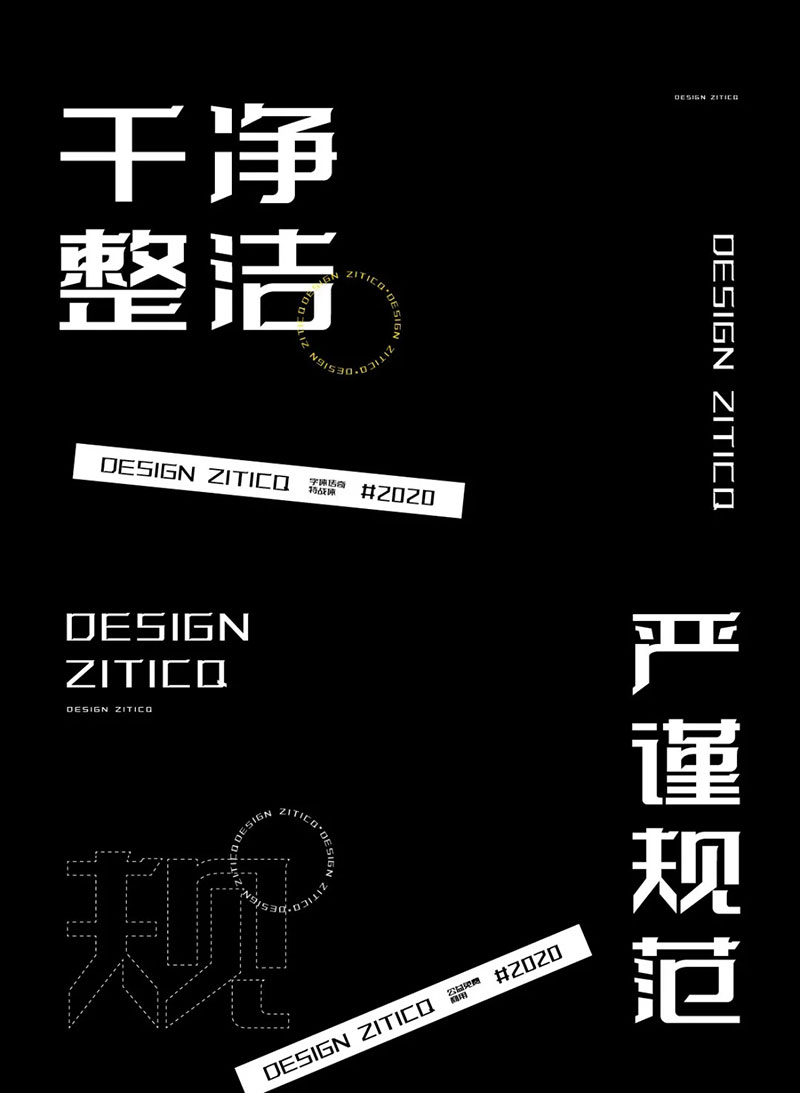
字體傳奇特戰體,根據GB2312編碼設計,整套字庫包含6763個簡體中文漢字,整體字形設計採用橫細豎粗的設計風格,橫線右端傾斜修飾,豎線右上角尖角修飾變形,整體視覺統一剛勁有力。
這款公益字庫,最早在2015年時,在群裡喊了幾十個人開發這款字,當時大家積極都挺高,給每個人分配好,要設計的字體內容後沒過多久,就聯繫不到參加的人了。可能是公益免費字庫設計,費時費力還不討好的事,這款公益字庫團隊就這樣散夥了。
直到2019年末,我才下定決心又在在群裡吆喝了一聲,做字庫的事情,這次我只找到了5位,願意做公益字體的小夥伴,其中有兩位是在家帶小孩子的小姐姐,還有兩位是一對情侶,一個在上班,一個在考研, 最後一個是00後的設計師,在加上我東拼西湊,這就是這個公益字庫的小團隊。當時正好趕到過年,大家都沒有出門,從初一下午就開始在設計,一直到五六月份才全部設計加修改完成。
沒有專職的設計團隊,就這樣湊齊了幾位小夥伴,一切都是熱愛設計才聚到一起,如果不是因為熱愛幾年前就放棄了這件事。由於人比較少,但做了一件很艱苦的事,我給這個小隊起名為,字體特戰隊,所以這款公益字庫,就起名為(特戰體)也是希望在設計的道路上,不懼困難和挫折,堅持夢想繼續戰鬥。
字體傳奇特戰體是一款微設計變形的字庫,微變形設計是我們平時在,商業案例和學習時的一些常用技巧,結合設計出的一套字庫,主要適合用於需要變形的,字體標誌主題應用領域等需要。整體字形結構,嚴謹-規範-乾淨-整潔。